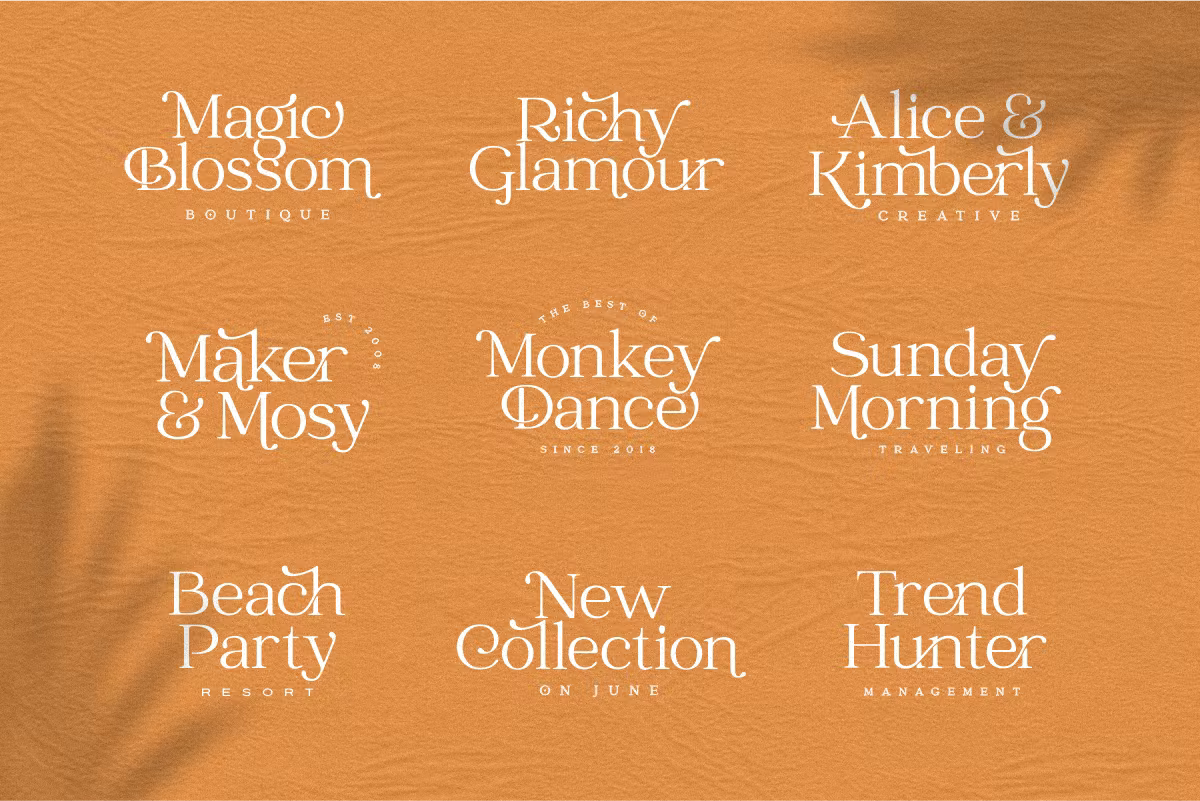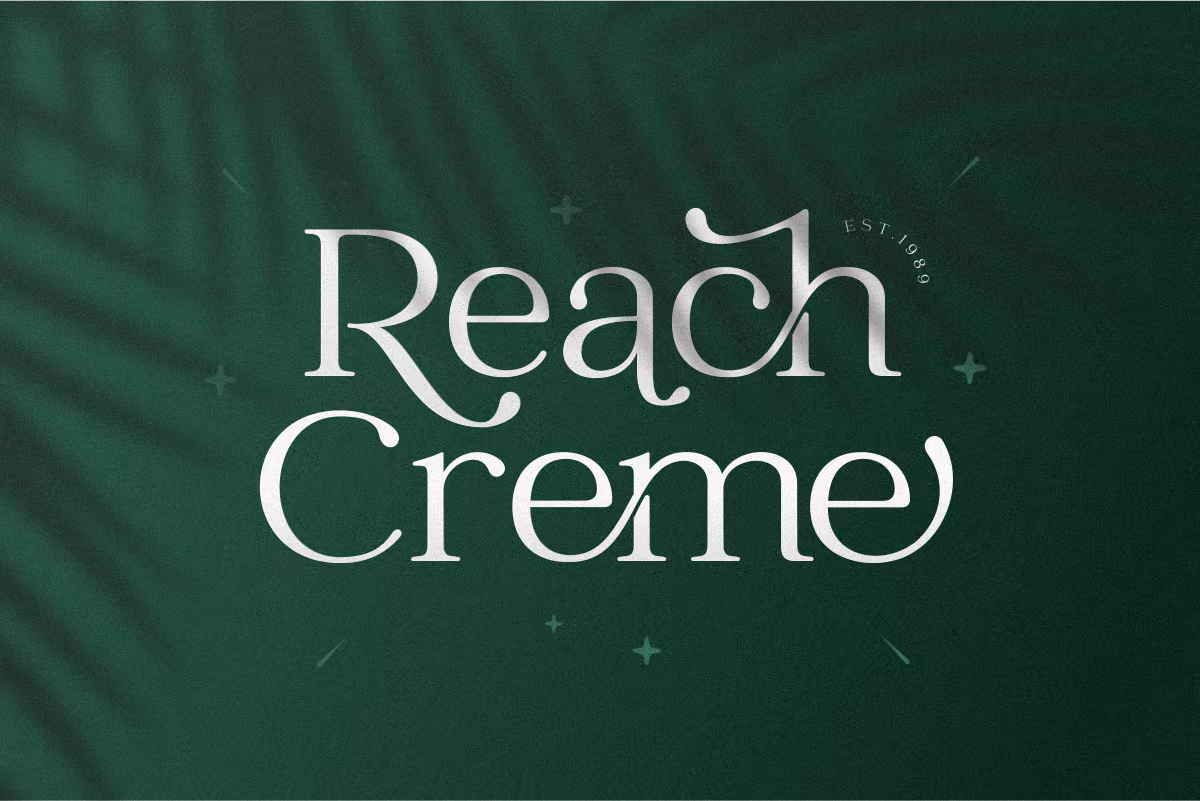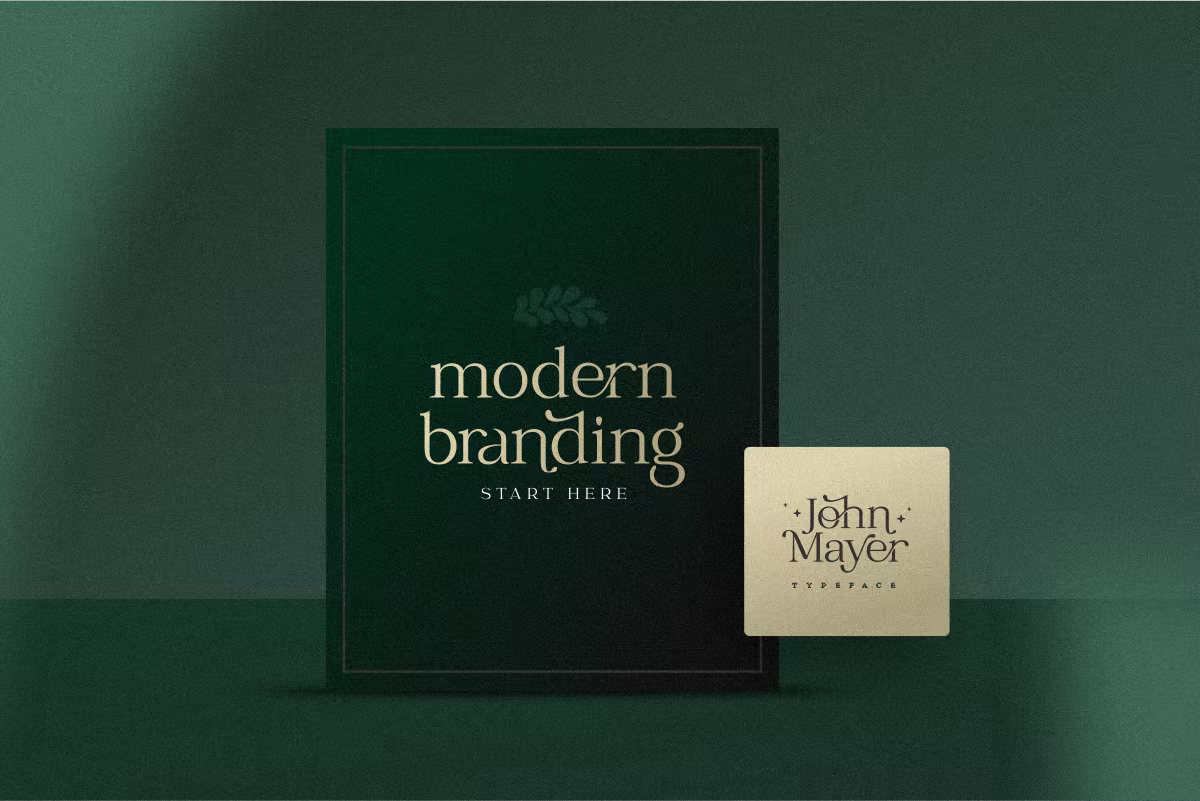
John Mayer Font
Description de John Mayer Font
John Mayer Font est une police unique et très élégante pour la conception de marques et de logos. Fort de notre expérience de graphiste travaillant pour de nombreuses entreprises, on nous demande souvent de concevoir un logo dans un style unique mais avec une forme élégante. Nous essayons donc de réfléchir et de créer cette police pour que l’idée soit diffusée. C’est parfait pour le BRANDING et la CONCEPTION DE LOGO. Vous obtiendrez des logos chics, élégants et certainement uniques avec cette police.